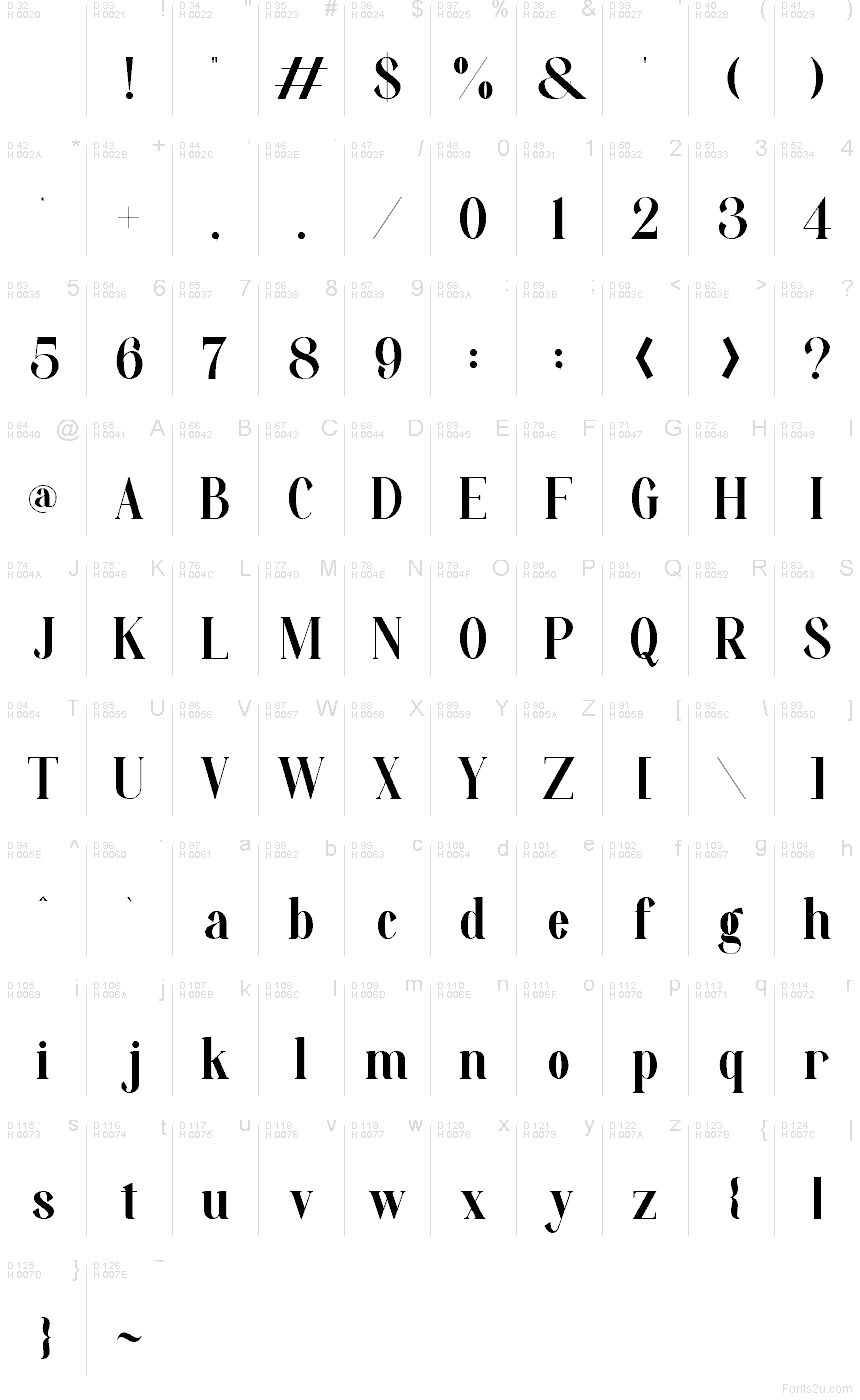
Vendita
Vendita od studia Ermedia Studio je bezplatné kontrastní patkové písmo s vysokými, úzkými proporcemi a výrazným vzhledem módního magazínu. Silné svislé tahy se v něm potkávají s mimořádně jemnými oblouky a příčkami. Dlouhé, štíhlé patky a úzce klenuté ovály dodávají literám formální ráz, zatímco ostré hroty vnášejí do hladkých křivek dramatický detail.
Pro módní a kosmetické značky představuje tato kombinace jasné směřování při tvorbě obalů parfémů i vizuální identity butiků. Přesvědčivé uplatnění nacházejí tyto litery také v časopiseckých titulcích. Ve všech těchto prostředích dodávají úzké proporce a extrémní kontrast tahů stejnou vytříbenou eleganci názvům produktů i redakčním textům.